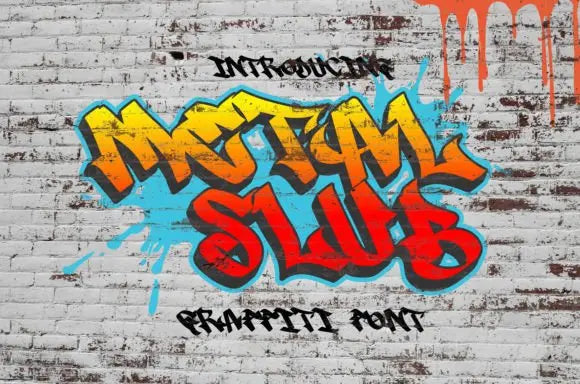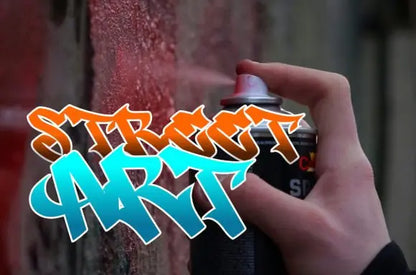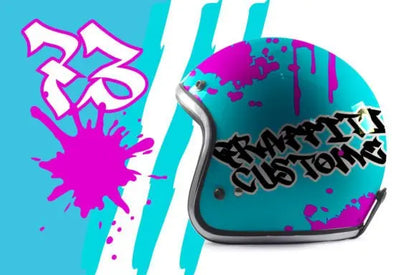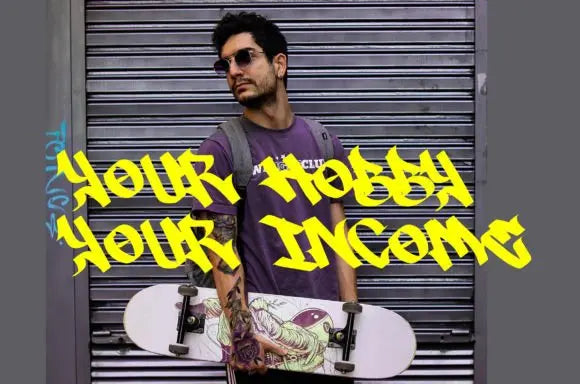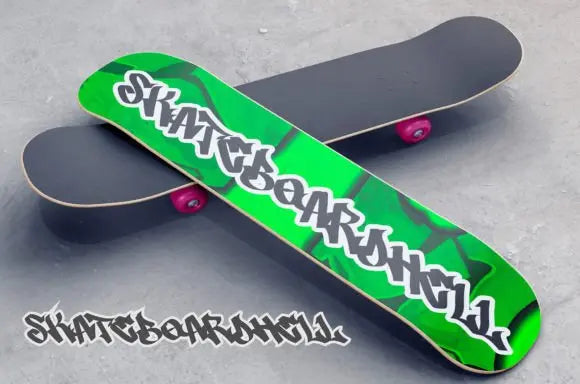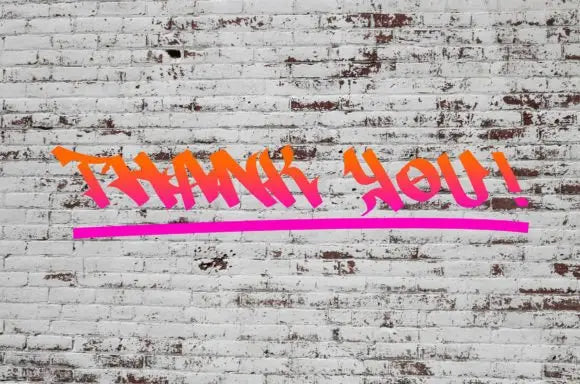
Fuente flameada de metal
Metal Slub es una fuente de visualización atrevida y de estilo urbano. ¡Agrega esta fuente asertiva a tus diseños y haz que se destaquen! Cree diseños que llamen la atención con la fuente Metal Slub, atrevida y moderna. Mejora tus proyectos y capta la mirada de tu audiencia.